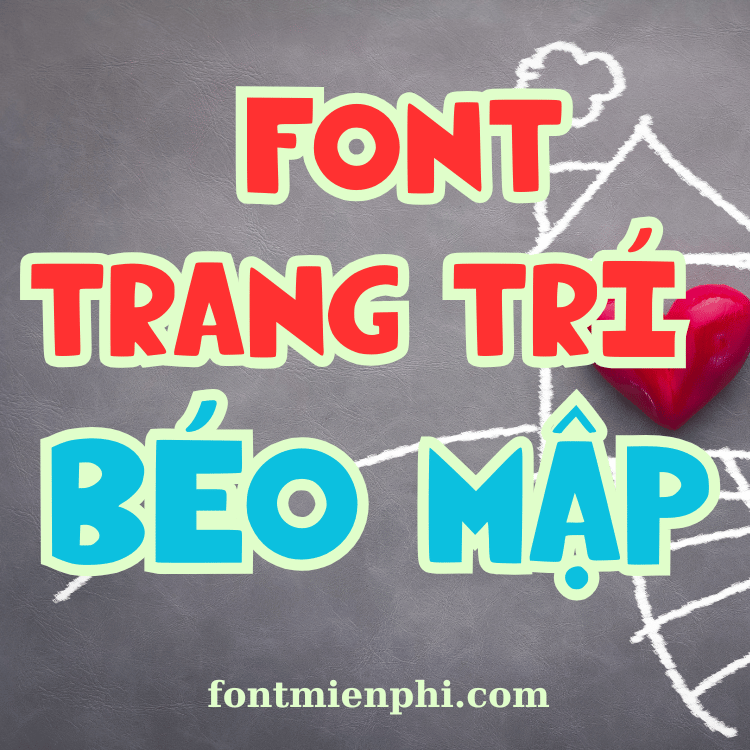
Font Novox Việt Hóa , Font thiết kế Béo Mập,font Thiết Kế Áo Thun
Tải Ngay Font Novox Việt Hóa – Font Thiết Kế Béo Mập Độc Đáo Cho Font Thiết Kế Áo Thun
Khám phá sức hút từ Font Novox Việt Hóa và ứng dụng trong sáng tạo
Trong thế giới đồ họa hiện đại, việc lựa chọn Font Miễn Phí phù hợp là yếu tố then chốt tạo nên sự thành công cho sản phẩm. Font Novox Việt Hóa nổi lên như một hiện tượng nhờ phong cách đậm nét, mạnh mẽ và vô cùng ấn tượng. Đây là mẫu Font thiết kế Béo Mập lý tưởng dành cho những ai muốn truyền tải thông điệp một cách trực diện và cá tính. Với các đường nét bo tròn đầy đặn, font chữ này mang lại cảm giác vui nhộn nhưng không kém phần chuyên nghiệp, giúp các tác phẩm trở nên nổi bật hơn bao giờ hết.
Tại sao nên chọn Font Novox Việt Hóa làm Font thiết kế Áo Thun?
Khi nhắc đến font Thiết Kế Áo Thun, yêu cầu quan trọng nhất là khả năng hiển thị rõ nét từ xa. Font Novox đáp ứng hoàn hảo tiêu chí này nhờ cấu trúc dày (bold) đặc trưng. Khi in ấn lên chất liệu vải, các nét chữ béo mập giúp hình ảnh không bị vỡ hay lu mờ. Đặc biệt, phiên bản Việt hóa đã được tối ưu hóa toàn bộ hệ thống dấu tiếng Việt, đảm bảo tính thẩm mỹ cao nhất cho người dùng tại Việt Nam khi thiết kế đồng phục lớp, áo nhóm hay thương hiệu thời trang cá nhân.
Ưu điểm nổi bật của Font thiết kế Béo Mập trong đồ họa
Mẫu Font thiết kế Béo Mập như Novox thường được ưu tiên trong các dự án đòi hỏi sự phá cách. Chúng tạo ra sự cân bằng tuyệt vời giữa nghệ thuật chữ và không gian thiết kế. Ngoài việc dùng làm font Thiết Kế Áo Thun, bạn còn có thể ứng dụng Novox vào làm tiêu đề poster, biểu ngữ quảng cáo hoặc bao bì sản phẩm trẻ em. Sự thân thiện trong từng đường cong giúp người xem cảm thấy gần gũi và dễ chịu hơn.
Cách sử dụng Font Novox Việt Hóa hiệu quả nhất
Để khai thác tối đa vẻ đẹp của Font Novox Việt Hóa, các nhà thiết kế nên kết hợp với những tông màu tương phản mạnh. Việc sử dụng các hiệu ứng đổ bóng hoặc viền chữ sẽ làm tăng thêm độ dày dặn và sức nặng cho thị giác. Hãy thử áp dụng ngay vào bộ sưu tập áo thun mới nhất của bạn để thấy sự khác biệt mà bộ chữ này mang lại.